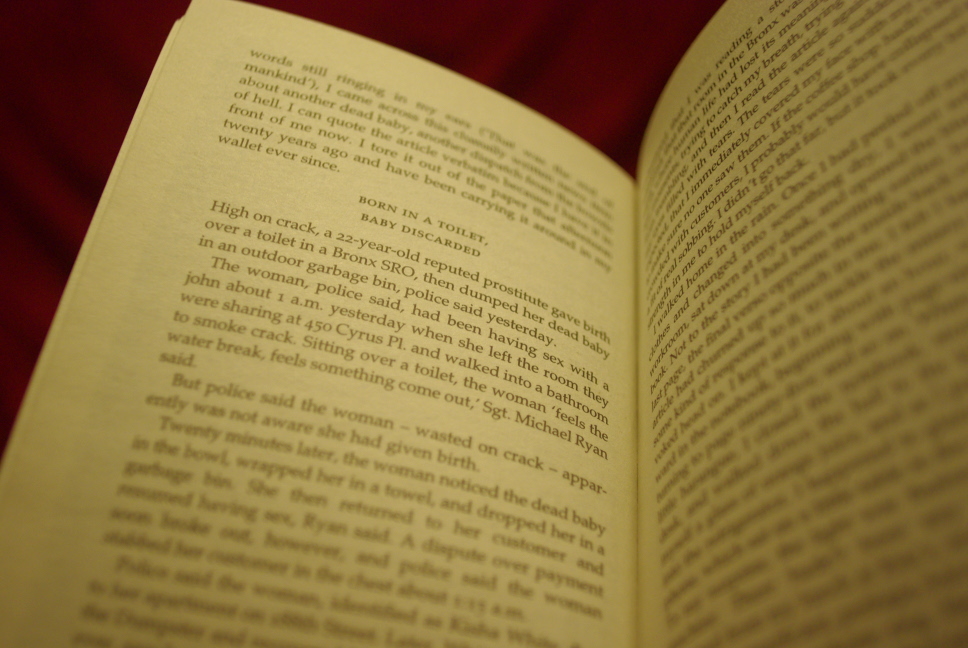
Suche Anwendungsbeispiele
Ich muss am Donnerstag ein Referat über die Schrift Palatino halten und suche noch dringend Anwendungsbeispiele... Habe schon etliche Versuche via Suchmaschine hinter mir, aber finde einfach nichts :( Lediglich den Verweis, dass Vanity Fair die Palatino in ihren Fließtexten verwendet.
Schön wäre allerdings wenn ich ein Beispiel hätte wo die Palatino nicht gerade als Fließtext dargestellt ist.
Vielleicht ist je einem von euch mal eine Werbung/Werbeanzeige oder ne Überschrift von irgendwas aufgefallen, bei der die Palatino benutzt wurde.
das problem is halt, dass die palatino meistens als fließtext schrift benutzt wird... daher findet man wohl auch nich so viel... wer weiß..
nee nee, die palatino ist auch als display-schrift markant genug, um sie beispielsweise in der werbung einzusetzen. mir fallen nur grad keine beispiele ein.
das "problem" mit der palatino ist eher, dass sie seit mitte der 80er jahre einfach überall auf jedem mac und später jedem PC (als book antiqua) verfügbar war und daher extrem oft verwendet wurde, so dass sie von designern seit dieser zeit gemieden wurde.
hier noch ein paar weitere anwendungsbeispiele:
... scheint so, als ob sie bei universitäten sehr beliebt ist.
Amerikanische und englische Verlage lassen gar nicht so selten in ihr setzen. Hier ein Beispiel aus einem von Faber and Faber verlegtem Taschenbuch.